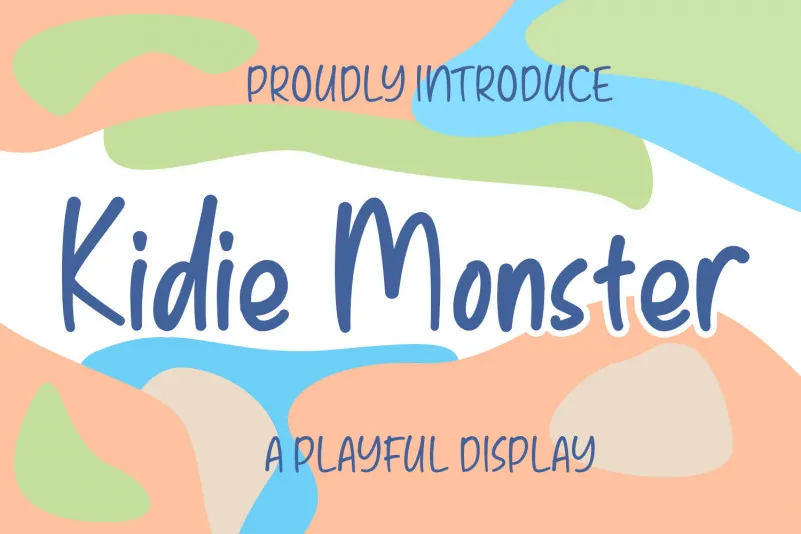
Descubra a magia de ‘Kidie Monster Font’ com essa fonte divertida e colorida que combina criatividade infantil e uma pitada de adulta modernidade. Seu uso é seguro e conveniente para projetos de jogos, livros de histórias infanto-juvenis ou qualquer trabalho onde a personalização do texto precisa ser engraçado e reconfortante. Esta fonte é ideal para pais que desejam transmitir uma mensagem divertida e amigável aos seus filhos. Também é perfeita para designers visuais, que buscam adicionar um toque único e criativo às páginas de histórias infanto-juvenis ou outros trabalhos educativos. Seja para projetos escolares ou até mesmo para personalizar lembranças infantis, a ‘Kidie Monster Font’ é uma ótima opção para tornar qualquer projeto ainda mais divertido e memorável.